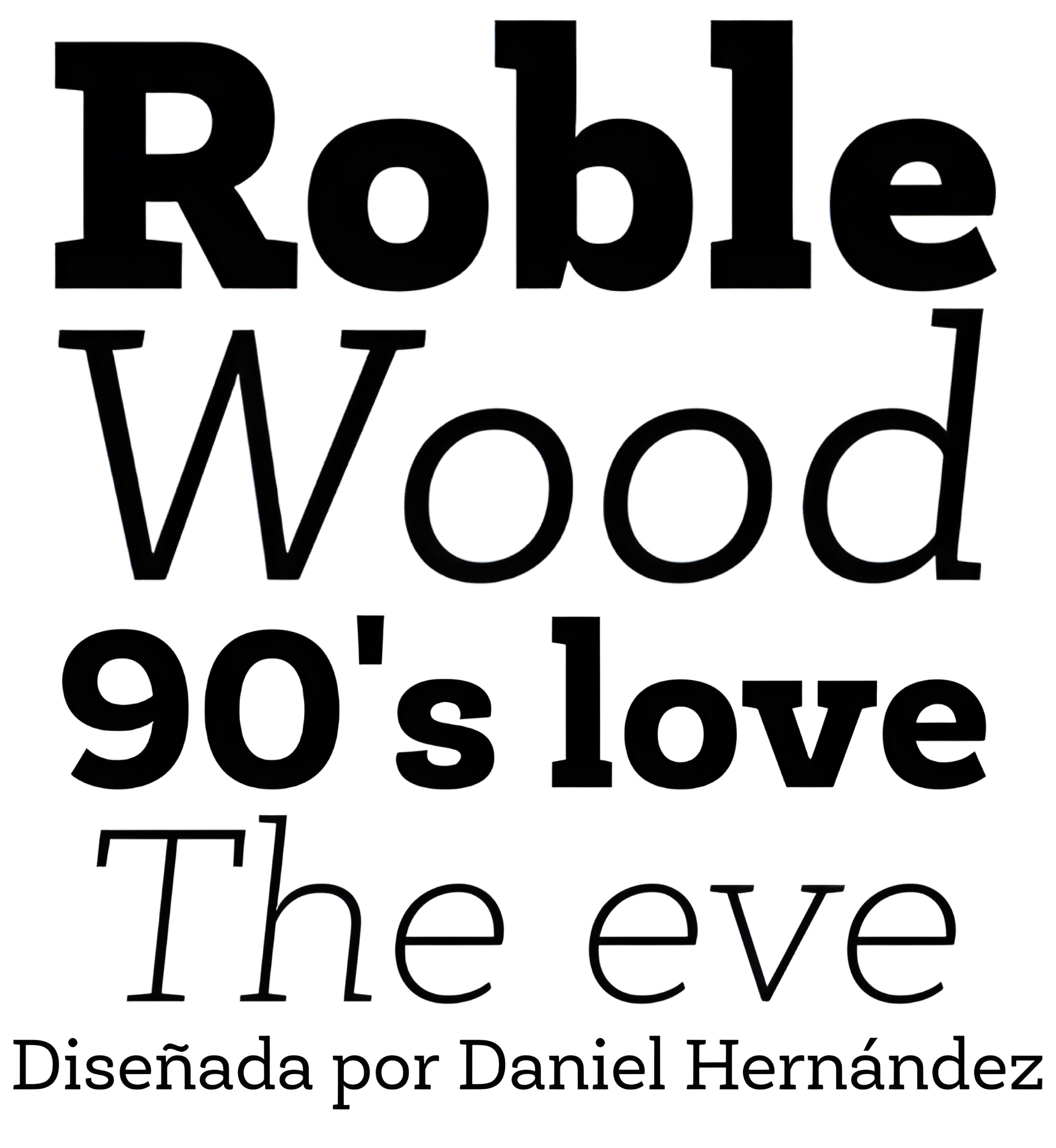
Roble
| Año | 2013 |
| Créditos | Daniel Hernández |
| Descripción | Roble es una Slab Serif Font, de una mezcla entre Andes y Sánchez. El resultado es una armonía entre las dos fuentes, una sin gracias y otra con gracias, con un resultado fresco y dinámico. Roble es una familia de 16 fuentes de 8 pesos más cursiva. |
| Familia(s) | Roble |
| Estilos | 16 |
| Estudio | Latinotype |